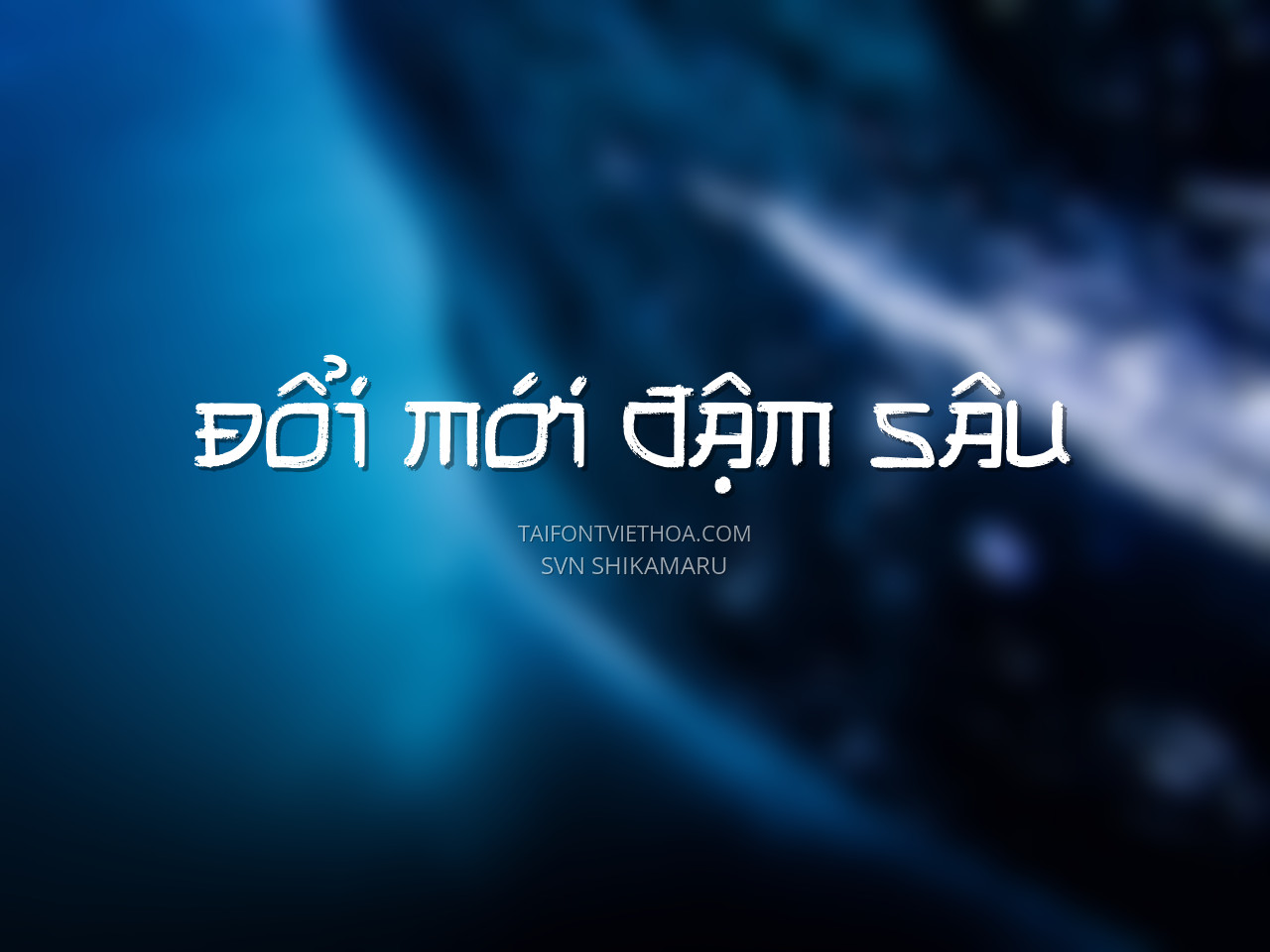
Font việt hóa SVN Shikamaru
Giới thiệu về Shikamaru – Font display Nhật Bản cá tính, đậm chất manga
Shikamaru (tên gốc: Shikamaru Typeface) là phông chữ display mang phong cách Nhật Bản hiện đại, được phát triển bởi Nurf Designs(Indonesia) và phát hành lần đầu trên Creative Market năm 2021. Lấy cảm hứng từ văn hóa manga, anime và các poster phim hành động Nhật Bản, Shikamaru sở hữu các đường nét góc cạnh, dứt khoát, cấu trúc chữ đậm và biến tấu mạnh về hình khối. Bản quốc tế hỗ trợ hơn 60 ngôn ngữ Latin, bộ ký tự đặc biệt, alternates và số học đầy đủ, giúp font phù hợp với đa dạng dự án sáng tạo – từ digital đến in ấn truyền thống.
Phiên bản SVN Shikamaruđã được STYLEno.1 FontsViệt hóa trọn bộ: bổ sung dấu tiếng Việt, cân chỉnh kerning, tối ưu hóa hinting giúp font hiển thị sắc nét ở mọi kích thước chữ. Đội ngũ taifontviethoa.comđã kiểm thử thực tế trên Photoshop, Illustrator, Canva…, đảm bảo không lỗi dấu, không vỡ nét, sử dụng linh hoạt cho các dự án thiết kế poster, bìa truyện, banner hoặc sản phẩm truyền thông gaming, anime, manga, truyện tranh.
Đặc điểm thiết kế, ứng dụng và ngành nghề phù hợp
Shikamaru thuộc nhóm display – phong cách Nhật Bản, với nét chữ đậm, góc cạnh mạnh mẽ, hình khối khỏe khoắn, tạo cảm giác hành động, năng động và trẻ trung. Bộ alternates, ký tự đặc biệt, số và ligature đa dạng giúp dễ dàng cá nhân hóa poster phim, truyện tranh, logo game, nhãn sản phẩm hoặc các dự án truyền thông dành cho giới trẻ. Font còn cực kỳ hiệu quả khi dùng trong các sản phẩm sáng tạo về manga, anime, gaming, sự kiện hoặc shop phụ kiện phong cách Nhật Bản.
Ứng dụng tiêu biểu
Poster & truyền thông:Poster anime, manga, banner sự kiện Nhật Bản, poster phim hành động, story social media.
Logo & nhận diện:Logo game, thương hiệu phụ kiện Nhật Bản, shop anime, sản phẩm văn hóa pop.
Bao bì & nhãn mác:Nhãn sản phẩm, hộp quà, sticker manga, sản phẩm handmade cho giới trẻ.
Ngành nghề phù hợp